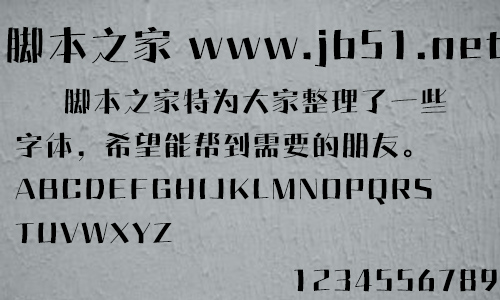
方正盈彩體由方正字庫出品的藝術字體,橫細直粗,橫劃,帶小許拋離弧形,直劃也是有小許弧度,全款字是沒有一條垂直平行線的,擺脫傳統(tǒng),適合應用于藝術設計、平面宣傳設計、網(wǎng)頁設計,書法字帖等領域。
盈彩體的創(chuàng)意靈感源于化妝品牌的宣傳,于是借著它發(fā)揮為一款創(chuàng)意字體, 由于宣傳內(nèi)容色彩繽紛,所以命名為“盈彩體”。盈彩體特點是橫細直粗,橫劃,帶小許拋離弧形,直劃也是有小許弧度,全款字是沒有一條垂直平行線的,擺脫傳統(tǒng)。盈彩體充滿動感和活力,多姿多彩,充分發(fā)揮女性魅力,它含8 款不同粗細字體!適用于化妝類,時裝類,體育類等商業(yè)宣傳和包裝設計。
方正盈彩體 簡 ExtraLight
方正盈彩體 簡 Light
方正盈彩體 簡
方正盈彩體 簡 Medium
方正盈彩體 簡 DemiBold
方正盈彩體 簡 Bold
方正盈彩體 簡 ExtraBold
方正盈彩體 簡 Heavy